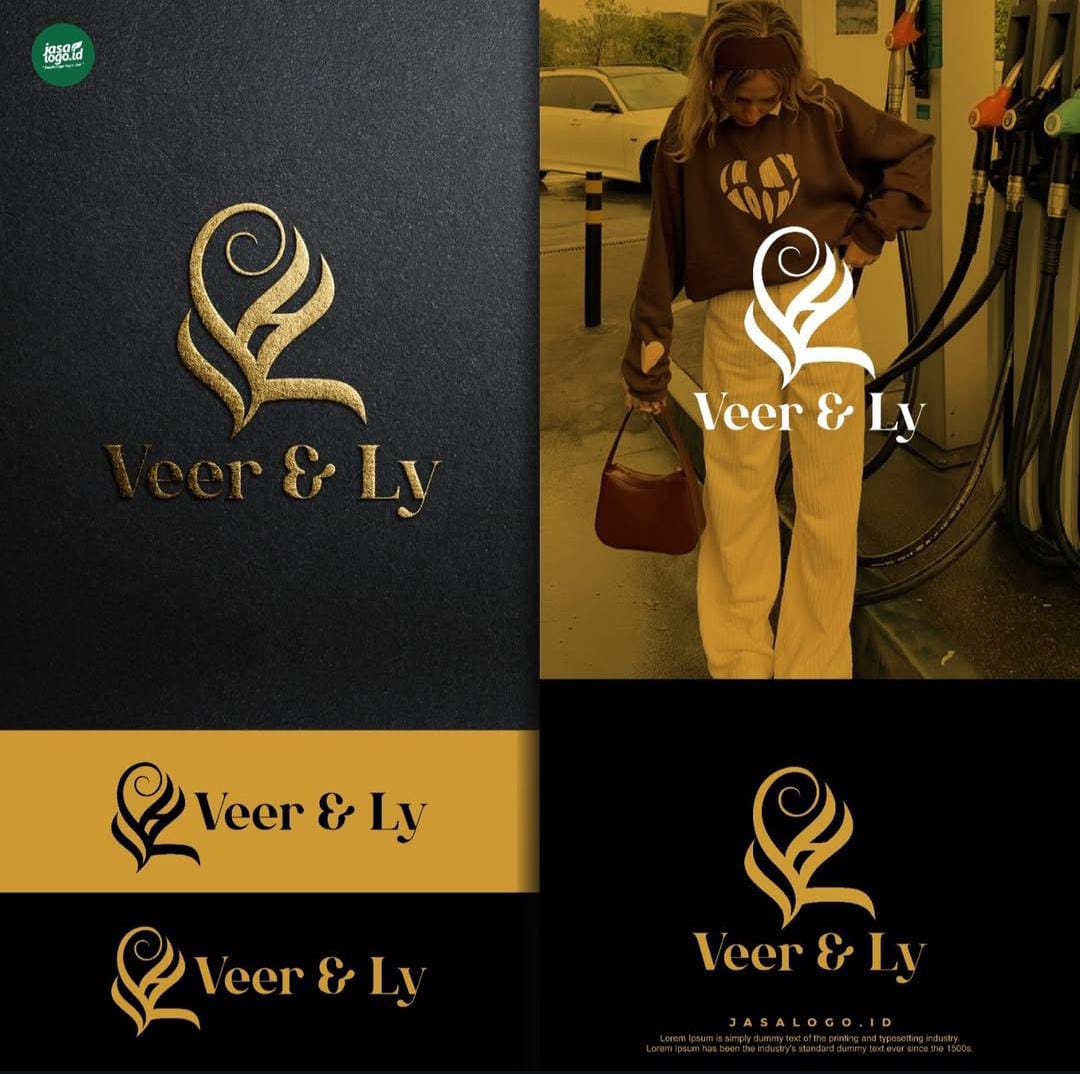
Font serif memiliki gaya serif yang bervariasi dapat menciptakan kesan modern, elegan, klasik hingga formal. Tipografi serif bisa menciptakan kesan sesuai citra dan identitas merek. Font serif bergaya klasik dalam desain logo bisa menciptakan kesan brand yang elegan dan vintage pada brand seperti bakery dan fashion.
FONT SERIF KLASIK
Pada umumnya font serif memiliki dekorasi ekor pada ujung huruf yang disebut serif, bentuk serif juga bervariasi. Pada serif klasik, bentuk serif ada yang tebal, tipis dan bulat, tetapi tidak lancip atau tajam. Hal ini karena serif klasik memiliki style seperti tipografi retro yang memiliki tekstur dan gaya vintage.
Secara umum gaya font serif klasik memiliki visual yang menciptakan kesan retro dan vintage, memiliki gaya huruf seperti:
Memiliki Serif yang Tidak Lancip
Jika serif modern memiliki style serif yang lancip dan tajam untuk menciptakan gaya modern. Style serif klasik memiliki bentuk serif yang agak bulat dan terkadang tebal sehingga lebih memiliki tekstur seperti gaya vintage.
Memiliki Huruf yang Kontras Tebal dan Tipisnya
Gaya huruf font serif klasik memiliki ketebalan huruf yang kontras sehingga tampil menarik. Biasanya batang huruf lebih tebal dibandingkan bagian huruf lainnya sehingga tampil unik.
Proprosi yang Seimbang
Gaya huruf-huruf pada jenis font serif klasik akan memiliki proporsi huruf yang simetris dan harmonis. Style hurufnya akan memiliki style seperti seni klasik sehingga menciptakan gaya huruf yang simetris.
Gaya Tradisional
Font serif klasik juga memiliki ciri khas dapat menciptakan kesan resmi, klasik dan mewah. Sehingga penggunaan font ini banyak ditemui pada surat kabar, majalah dan desain buku.
Memiliki Ornamen
Terkadang serif klasik beberapa diantaranya memiliki ornamen klasik seperti serif yang memanjang dan melingkar-lingkar. Serif klasik juga memiliki tekstur sehingga garis tidak selalu terkadang bertekstur sehingga seperti tulisan klasik. Hal ini membuat font memiliki visual yang lebih artistik.
DESAIN LOGO FONT SERIF KLASIK
Pada desain logo, font serif yang memiliki style klasik dan vintage akan mencerminkan kesan brand yang formal, tradisional dan elegan. Biasanya jika ingin menciptakan brand yang elegan dan premium bisa menggunakan style serif klasik. Berikut beberapa contoh desain logo dengan font setif klasik yang sederhana:
Logo Selaras Anugerah Walet
Tipografi yang digunakan dalam desain logo perlu mengutamakan keterbacaan nama brand sehingga membangun identitas yang kuat. Sehingga penggunaan font serif klasik pada logo tersebut bisa memudahkan teks dibaca dan mencerminkan kesan brand yang premium. Desain logo menggunakan style logo inisial sehingga hanya fokus pada gaya tipografi yang mencerminkan identitas merek.
Logo tersebut memiliki nama brand yang cukup panjang sehingga font serif agar mudah dibaca dan dapat mencerminkan identitas merek. Font serif klasik yang digunakan berhasil mencerminkan identitas brand yang premium, klasik dan sederhana. Serif klasik membuat desain brand makanan memiliki kesan premium dan elegan.
Logo Qimos Daycare
Gaya font serif memang diutamakan untuk menciptakan kesan visual yang elegan sehingga membangun kepercayaan publik. Pada desain logo untuk daycare tersebut gaya huruf yang tampil formal dan klasik mencerminkan kesan terpercaya. Font serif yang digunakan juga memiliki style sederhana sehingga harmonis dengan ikon inisialnya.
Gaya huruf yang sederhana memudahkan nama brand dibaca dan mendukung desain tampil minimalis. Font serif juga harmonis dengan logo inisial yang hanya berupa garis sederhana dibentuk huruf inisial yang unik. Selain meningkatkan keterbacaan, font serif logo daycare berguna mencerminkan bisnis terpercaya.
Logo Hello Skin
Desain logo yang cocok untuk font serif klasik yang elegan termasuk untuk brand kecantikan yaitu skincare dan kosmetik. Gaya huruf pada desain logo tersebut memiliki style huruf ketebalan yang kontras pada batang dan bagian huruf lainnya. Kontras garis dalam gaya huruf tersebut menciptakan gaya klasik yang menarik.
Style font serif yang agak tebal tersebut memiliki desain yang sederhana dan berkesan halus sehingga tampil elegan. Gaya font ini cocok mencerminkan logo skincare yang elegan. Font yang tebal pada logo tersebut memudahkan untuk dibaca dan tampil elegan mencerminkan jenis brand.
Logo Hervina Mua
Gaya font serif klasik juga bisa digunakan dengan style huruf yang tipis sehingga tampil elegan. Desain logo bisnis make up artis tersebut memiliki style desain yang elegan sehingga cocok menggunakan font serif klasik. Style font serif klasik pada logo tersebut memiliki ciri khas serif berbentuk kotak dan lebih panjang.
Gaya huruf klasik menciptakan logo berkesan elegan, klasik dan tampil sederhana. Nama bisnis juga mudah terbaca karena memiliki style huruf tipis, meski serifnya kaku. Ikon logo inisial juga menggunakan style serif klasik yang elegan sehingga harmonis dengan font serif yang digunakan.
Jenis fashion jas formal dan dress formal akan relevan menggunakan font serif klasik yang sederhana dan bersih. Font serif klasik dapat dikombinasikan dengan sesama font serif yang lebih modern atau sans serif sederhana.
Ada banyak gaya font serif yang bisa digunakan mencerminkan identitas berbagai jenis brand. Gaya font serif klasik memiliki style huruf yang bisa menciptakan kesan nostalgia dan formal. Untuk desain logo pastikan memilih jenis font serif yang memiliki keterbacaan yang baik sehingga nama merek mudah diingat.